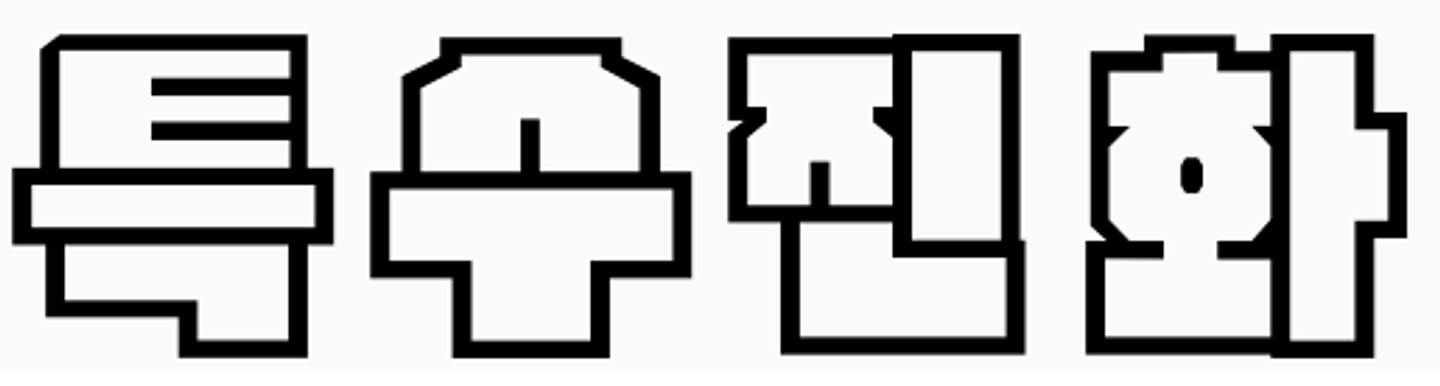
제가 옛날에 썼던 폰트인데 폰트 이름을 잘 모르겠습니다 분명 편집으로 속을 뚫은 폰트가 아니라 저 모양 그대로 나오는 폰트였습니다
양재블럭체
친근하고 귀여운 손글씨 스타일: 정돈된 디지털 폰트보다는 사람이 손으로 직접 쓴 듯한 자연스럽고 따뜻한 느낌을 주는 서체입니다. 둥근 모서리 처리: 거의 모든 획의 끝부분이 각지지 않고 부드럽게 둥글게 처리되어 있어 전체적으로 유하고 다정해 보입니다. 일정한 굵기: 각 글자를 구성하는 획의 굵기가 대부분 일정하며, 굵은 붓펜이나 두꺼운 사인펜으로 쓴 듯한 안정감을 줍니다. 높은 가독성: 손글씨 스타일임에도 불구하고 각 자음과 모음의 형태가 뚜렷하게 구분되어 있어 읽기가 매우 쉽습니다.